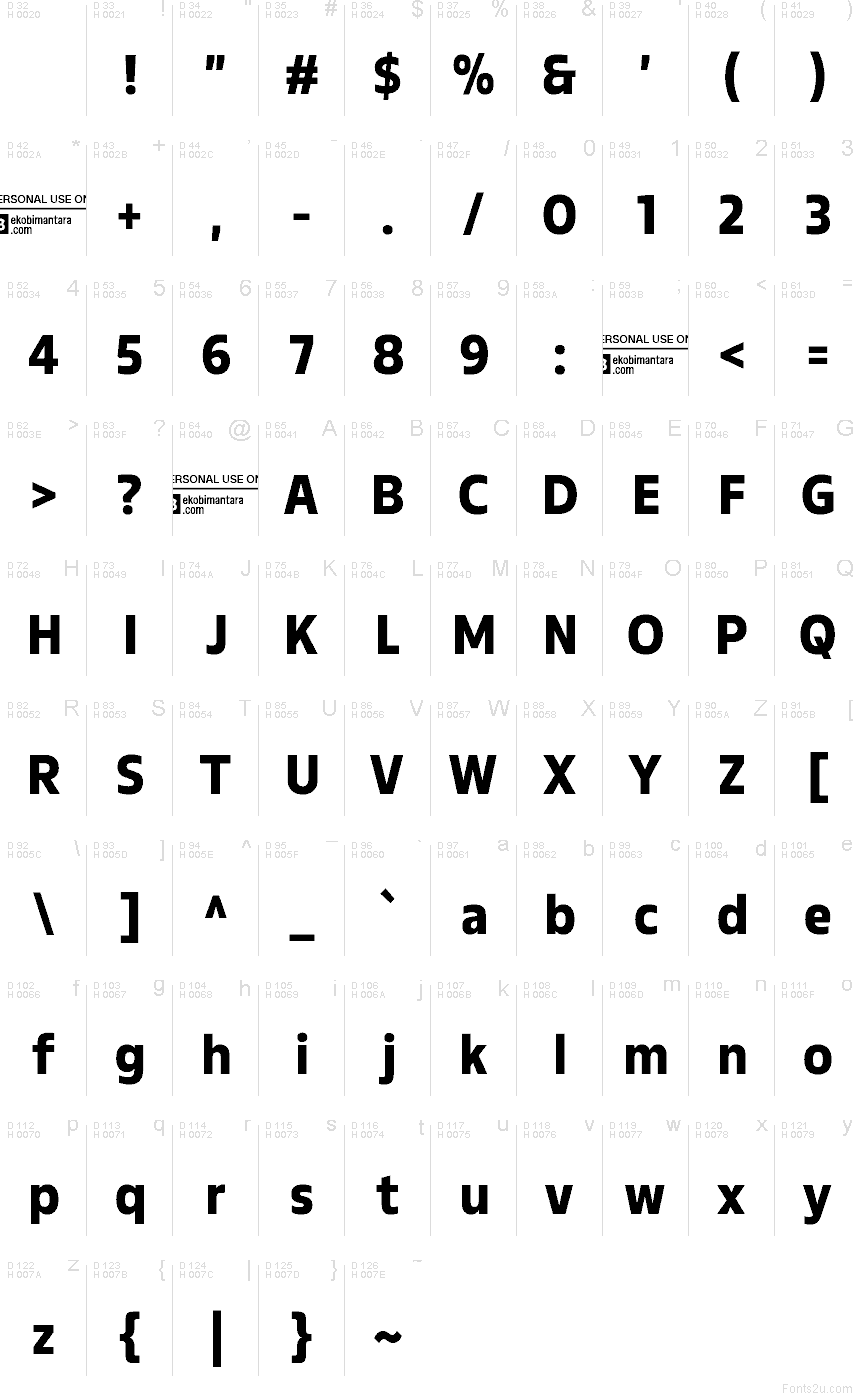
Profa Trial ExtBd Cond od Eko Bimantary je bezplatné úzke bezpätkové písmo s hutným, výrazným vzhľadom a moderným redakčným nábojom. Písmená sú husto vysádzané, so širokými ťahmi, hranatými okrajmi a jemnými krivkami, ktoré zjemňujú celkovú hmotnosť a dodávajú písmu rytmus s priamym, mestským charakterom.
Ideálne sa hodí na titulky plagátov, obálky časopisov, športovú grafiku, hudobné obaly a príspevky na sociálne siete, kde krátke slová potrebujú dôraz a údernosť. Ako bezplatné písmo sa skvele hodí aj na titulkové karty a kompaktné slovné logá. Použite ho vtedy, keď chcete dosiahnuť veľký efekt na veľmi malom priestore, pretože zúžená šírka a výrazná hrúbka urobia väčšinu práce za vás.